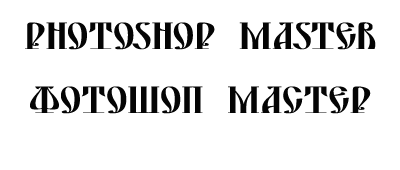
Шрифт - DS Yermak
Интересный шрифт, который хорошо подходит для работы в фотошопе. Есть поддержка русского языка.
Кстати большая часть работы пропала такой шрифт немного редкий поэтому как и в nescide там нет буквы ы и препинаний кстати вы можете поставить букву ы и знаки препинание с другим шрифтом
Шрифт замечательный в целом, но вот эти палочки снизу явно лишние
Буква Ы не работает...
Шрифт красивый респект :) уважаю вас а новый там цифровой не оч :(
буквы "ы" нет(((
XIX век
жаль буковки Ы нет
Очень красивый шрифт!!!!
А где в Вашем алфавите буква "Ы" и знаки препинания?
Каким интересно образом его датировали?